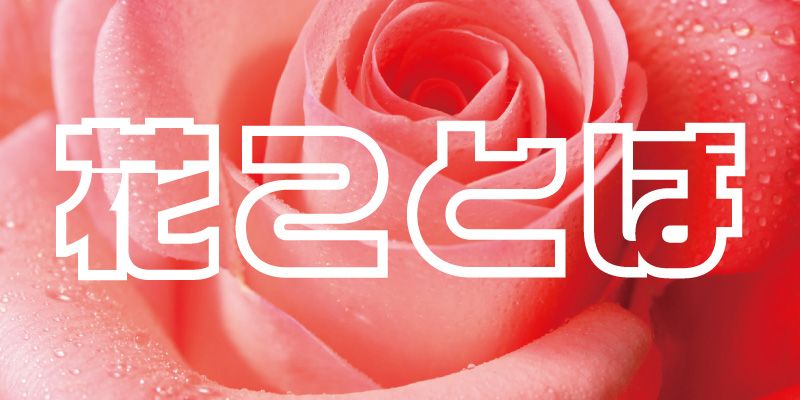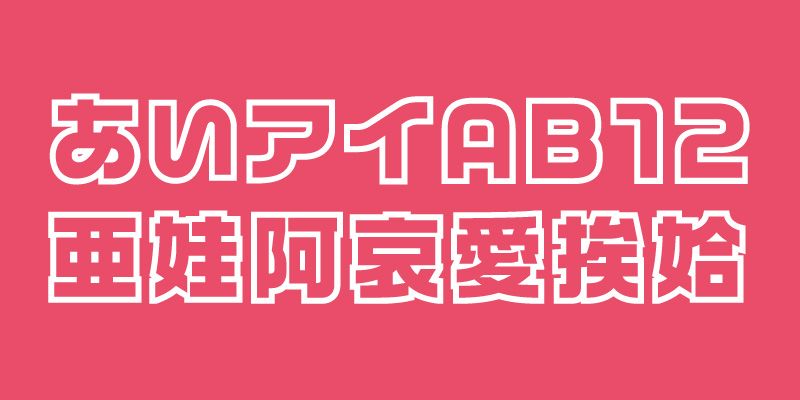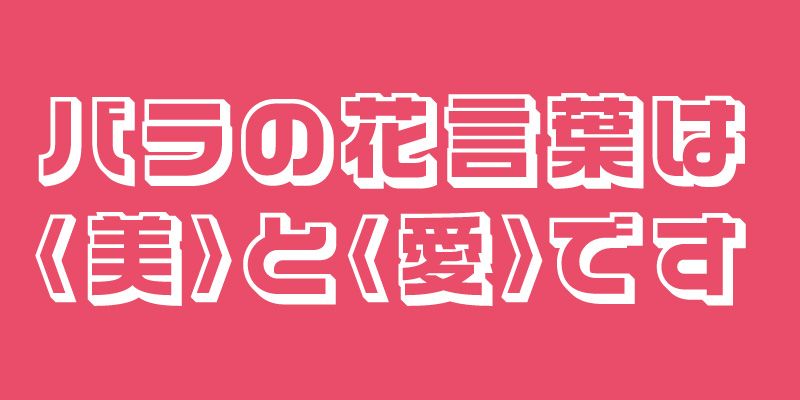
VDL-LogoJr-pop ist eine dekorative Schriftfamilie, die auf dem Design von VDL-LogoJr basiert.
Die Schriftfamilie besteht aus VDL-LogoJr-pop-FutoLine mit betonten Konturen und VDL-LogoJr-pop-Shadow mit schattierten Konturen mit einem 3D-Effekt.
Als Display-Schrift enthält jede Schrift 9.354 Glyphen (basierend auf der Adobe-Japan1-3 Character Collection).
Diese Schrift ermöglicht es dem Benutzer, eine breite Palette von Arbeiten mit visuell wirkungsvollem Ausdruck in den Bereichen Redaktion, POP-Display-Designs, Bildbearbeitung und Produktion von Videoinhalten zu kreieren.